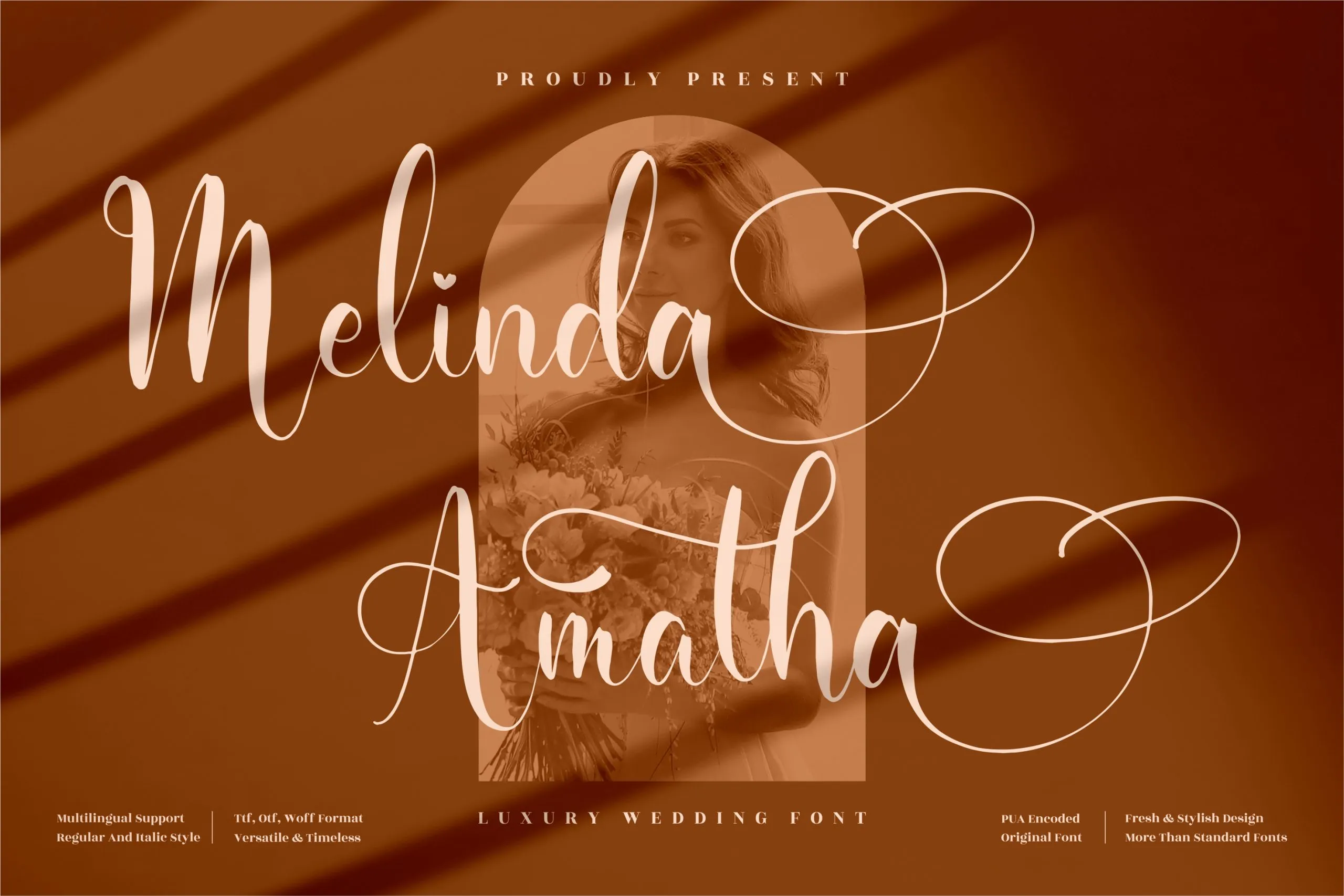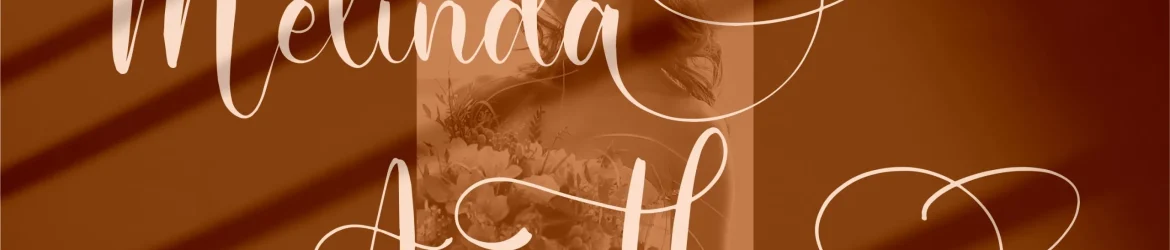
A ‘Melinda Amatha Font’ é uma delíciamente romântica escolha para qualquer projeto que exija um toque delicado e elegante. Seja um logotipo, design de marca, design de móveis de casa, embalagens de produtos, taças personalizadas, cartões de apelo ou até mesmo camisas personalizadas, esta fonte do tipo caligrafia é perfeita para dar um toque especial aos seus trabalhos. Ela também faz a sua vez em qualquer projeto que demande uma escritura delicada e poética como etiquetas, embalagens de fotografias, água-marinhas, anúncios especiais e até mesmo cartões de convite ou cartão de visita. A fonte é tão versátil quanto a criatividade de seus projetos.